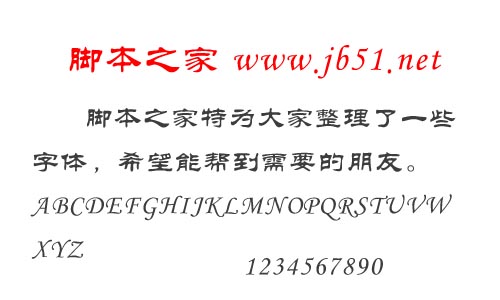
倉(cāng)頡劉隸簡(jiǎn)體是倉(cāng)頡字庫(kù)推出的一款藝術(shù)字體,風(fēng)格比一般的字體更有特色,連貫字跡顯得干練而不凌亂,清新簡(jiǎn)明,具有很好的視覺(jué)感,適合應(yīng)用于藝術(shù)設(shè)計(jì)、平面宣傳設(shè)計(jì)、網(wǎng)頁(yè)設(shè)計(jì),書法字帖等領(lǐng)域,歡迎喜歡倉(cāng)頡劉隸簡(jiǎn)體的朋友前來(lái)下載使用。